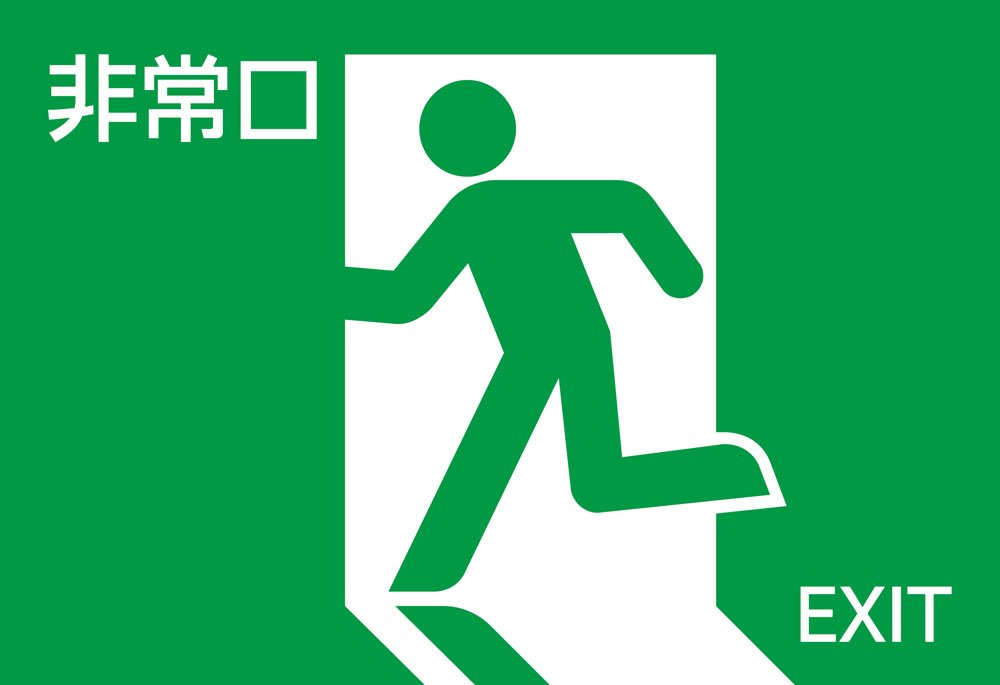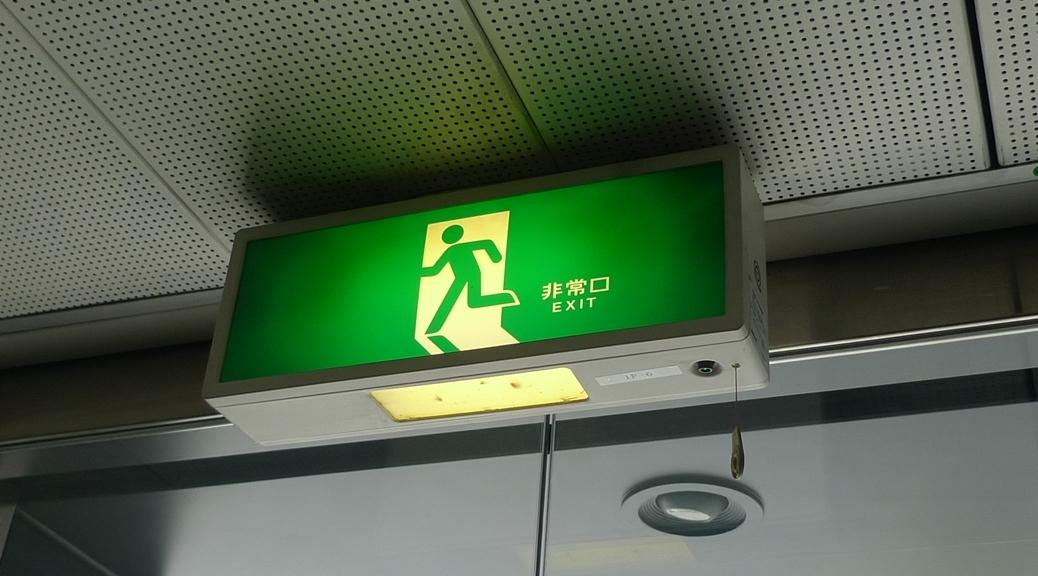
Japanische Schriftzeichen nach Vorlage tippen
kennt jemand einen einfachen Weg, um japanische Schriftzeichen einzutippen?
Ich hätte da eine Vorlage, bei der die japanischen Zeichen genau nach Vorlage abgetippt werden sollen.
Frag mal Norbert P …
Und bis der soweit ist, hier mal der Output von eben mal schnell ergoogelten Online-OCR-Tools. Ist natürlich nicht 1:1 korrekt, aber eine ganze Reihe von Zeichen scheinen schon mal zu stimmen.
1. versuch
量涙帯
彗F常囗丿丶ン卜“Jレを止まるまて弓ーLプ
卜^ア丿丶ン卜'丿レを ~~開" 方向へ9〇 〝L丈上まわせ
卜〝アを弓ーき出せ
2.versuch
非 寓
非常ロハンドルを止まるまて引け
卜'アハン卜'」レを “開" 方旧へ9〇 〝以上ま杓せ
ドアを引き出せ
非常口 hieße Emergency Exit.
Wenn man Kana und Kanji nicht lesen (=identifizieren) kann, würde ich's so machen, wie von Þorsten vorgeschlagen: OCR und dann die paar Zeichen, die nicht stimmen, ersetzen. Wobei das dann für "Unkundige" mit den Kanji schwierig sein dürfte.
Oder, falls es wirklich nur die paar Zeilen sind, einfach das hier kopieren:
非常口
非常口ハンドルを止まるまで引け
ドアハンドルを “開” 方向へ90°以上まわせ
ドアを引き出せ
Und was bei mir bei Vorlagen, die jedes OCR unmöglich machen, z.B. ein Tattoo-Foto, wo sich der Tattoo-Künstler mit Chinesisch, Koreanisch oder Japanisch versucht hat, ist der Google-Übersetzer.
Hier kann man nämlich die ostasiatischen Schriftzeichen sogar recht stümperhaft nach malen, bekommt dann eine Auswahl von Zeichen, wo man seines recht gut identifizieren kann, und gleich eine Übersetzung des Textes, um dessen wahrscheinliche Richtigkeit zu prüfen.
Wenn dann statt dem "Ich liebe dich"  dann "Nudelsuppe"  heraus kommt, ist wohl was daneben gegangen...
Mit dieser abmal-Technik (meine japanischen maus-gezeichneten Buchstaben waren echt grausam) bin ich zu diesem Ergebnis gekommen:
非常口
非常口ハンドルを止まで引ルナ
ドアハンドルを "開" 方向へ90° 以上まわせ
ドアを引き出せ
Man beachte hier das 4. Zeichen der vorletzten Zeile, das in der Vorlage noch so einen Punkt hat, und sich so vom 5. Zeichen in der Zeile darüber unterscheidet, ergab in der Übersetzung dann gar keinen Sinn.
Übersetzung dazu:
emergency exit
Pull out the emergency exit handle until it stops
Move the door handle more than 90 ° in the "open" direction
Pull out the door
das 4. Zeichen der vorletzten Zeile
Das ist ein n (aus "ha-n-do-ru", "handle").Und ich seh da im Original auch keinen Punkt ?!?
In der PDF-Datei? - Ach shit... Da klebt n Fliegenschiss auf meinem Bildschirm... genau so ein kleines Strichlein, wie in manchen Buchstaben... Muss wohl mal meinen Bildschirm putzen :-(
Sogar doahandoru (doorhandle) … Kommt vor, es gibt auch Lehnwörter aus dem Deutschen, z. B. ryukkusakku (laut Google-Übersetzer allerdings synonym auch bakkupakku und nappusakku, also Rucksack/backpack/knapsack). Soweit ich weiß, sind solche Lehnwörter (und ausländische Namen) daran zu erkennen, daß sie in Katakana geschrieben sind.
Das sieht ja schon mal alles sehr gut aus:
Das einzige, was mich etwas irritiert, ist dieses Zeichen:
Es hat bei der Vorlage keine Stege. Das liegt an der Schriftart, oder?
Gefordert ist die Schriftart "Gothic".
Damit ist hier "Serifenlos" gemeint, richtig?
Das einzige, was mich etwas irritiert, ist dieses Zeichen:
Es hat bei der Vorlage keine Stege. Das liegt an der Schriftart, oder?
Ich vermute eher, dass die Stege in der Vorlage vergessen wurde. Es gibt im Japanischen auch das Zeichen ohne die Stege.
Laut Google Übersetzer:
ロ Ro
口 Mund
囗 A
@bertel: Genau, Gothic "serifenlos"
Hmm, dann wurden die Stege wohl wirklich vergessen.
Vielleicht kann Norbert P das klären? Ich hab nur japanisches Google-Wissen … ;-)
Das dürfte daran liegen, dass es sich hier um so eine Singleline-CAD-Vektorschrift handelt, da sind viele Schriftzeichen recht vereinfacht dargestellt. Da schaut so manches nicht so aus, wie in anderen japaniscen Schriften. Ich habe mir mal japanische Notausgangsschilder in der Google Bildersuche angeschaut, da hat diese Glyphe zumeist die kleinen Füßchen. in selteneren Fällen, wo die schrift besonders grafisch glatt gemcht ist, fehlen die auch schon mal
Erster Google-Treffer:
Es scheinen beide Varianten im Umlauf zu sein. Welche nun richtig ist, weiß ich nicht.:-?
vor 6 Stunden schrieb catfonts:
der Google-Übersetzer.
Hier kann man nämlich die ostasiatischen Schriftzeichen sogar recht stümperhaft nach malen, bekommt dann eine Auswahl von Zeichen
Keyboard-Apps für ostasiatische Sprachen auf Smartphones und Tablets bieten oft eine ähnliche Funktionalität – falls Google mal versagen sollte.
Die "Füßchen" sind stylistische Elemente, ob mit oder ohne macht nix in Bezug auf die Bedeutung. Das kleine Kästchen (b in bertels Liste)  ist ein Katakana (ro) und wäre beim Notausgang falsch. Richtig ist der "Mund". So wie oben im Text zum Kopieren.
Ich würde mal sagen, ja.
Liegt das auch an der Schriftart?
Ja. Die zwei Striche machen aus dem てte ein でde (ein Kreis macht z.B. aus einem はha ein ぱpa, die Striche dann ein ばba.). Der Platz ist (irgendwo) rechts oben, aber das wird von den Schriftdesignern halt "interpretiert".
Eine echt komplizierte Geschichte :-)
Aber dann passt ja alles.